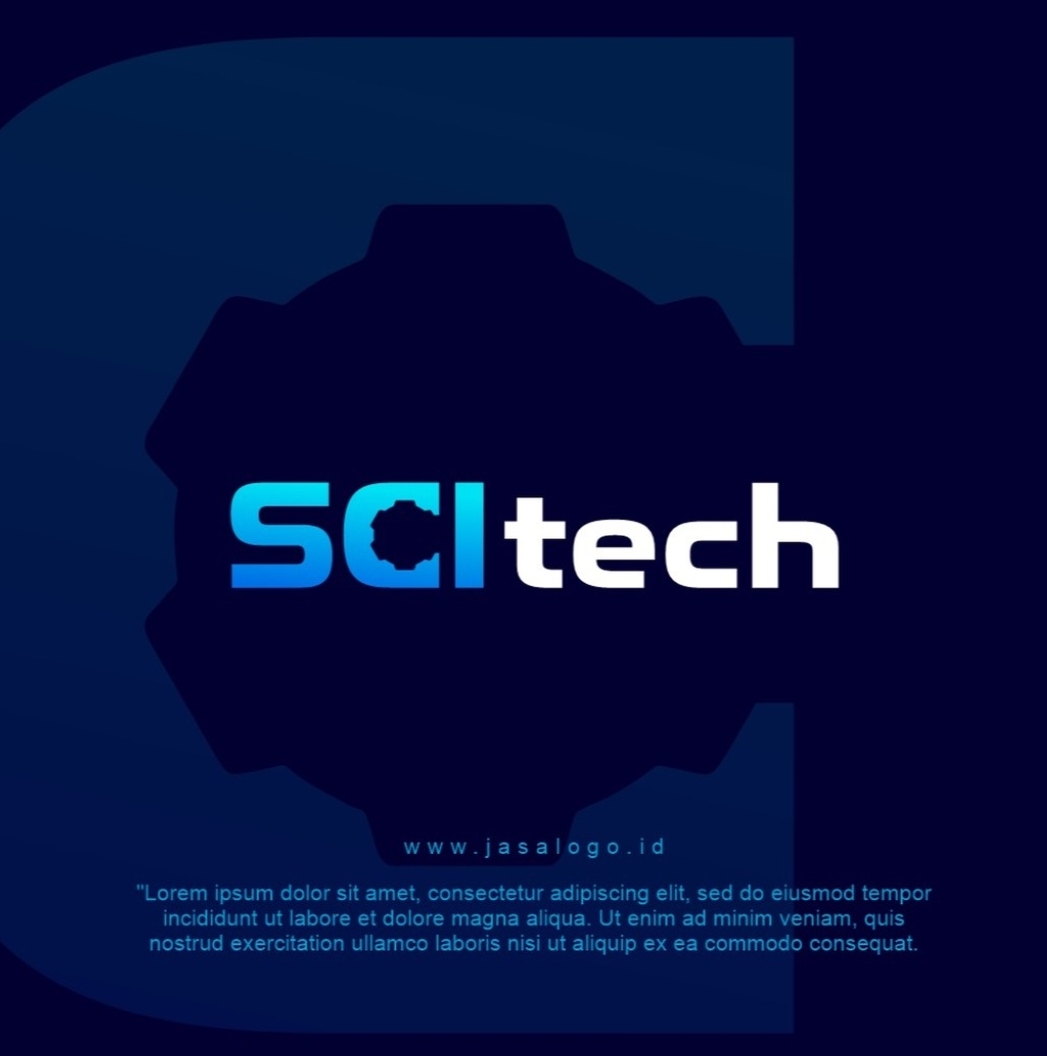
Desain logo harus memiliki gaya font yang relevan sehingga bisa mencerminkan identitas merek serta jenis brand dengan baik. Ada banyak pilihan gaya font untuk berbagai jenis brand dan karakternya seperti tebal, tipis, miring hingga unik. Untuk digunakan dalam desain logotype, ada banyak rekomendasi font yang menarik dan mencitrakan identitas brand.
Biasanya rekomendasi font untuk desain logotype akan mengutamakan keterbacaan dan bentuk huruf yang menciptakan kesan sesuai jenis brand. Brand yang menggunakan logotype bertujuan untuk membangun identitas yang kuat dengan membuat audiens mengingat nama brand. Untuk itu pemilihan gaya font untuk brand yang sering menggunakan logotype harus dipertimbangkan dengan baik.
REKOMENDASI GAYA FONT UNTUK JENIS LOGOTYPE SEUSAI BRAND
Untuk menciptakan desain brand yang bisa merepresentasikan brand dengan baik penting untuk memilih jenis font dan gaya font yang sesuai citra brand. Bahkan dalam bidang yang sama jika produk brand berbeda akan membutuhkan jenis font yang berbeda. Berikut beberapa rekomendasi font untuk desain logotype yang sesuai jenis brandnya:
- Rounded font untuk Logo Minuman
- Bold and Clean untuk Logo Teknologi atau perusahaan
- Sertif Elegan untuk Logo Fashion and Beauty
- Script untuk Logo Wedding dan Jewelry
- Wavy font untuk brand minuman
- Sans serif untuk Logo Perusahaan
- Condensed untuk Logo Teknologi
Beberapa rekomendasi tersebut hanya memilih gaya font yang paling digunakan dan sering ditemui untuk setiap brand tersebut. Terkadang brand bisa memilih gaya font yang tidak umum untuk tampil beda seperti penggunaan font serif elegan untuk minum segar. Pemilihan font tidak hanya berdasarkan jenis produk atau brand tetapi juga berdasarkan identitas merek.
CIRI FONT SETIAP JENIS BRAND
Ada banyak sekali jenis brand yang menggunakan jenis logotype, setiap brandnya memiliki ciri khas font tersendiri untuk mencerminkan identitas bisnis. Pemilihan gaya font akan cukup memengaruhi kesan dan pesan yang ingin disampaikan melalui logotype. Setiap jenis brand akan memiliki ciri-ciri atau karakteristik font yang cocok dengan citra brand tersebut.
Brand Makanan
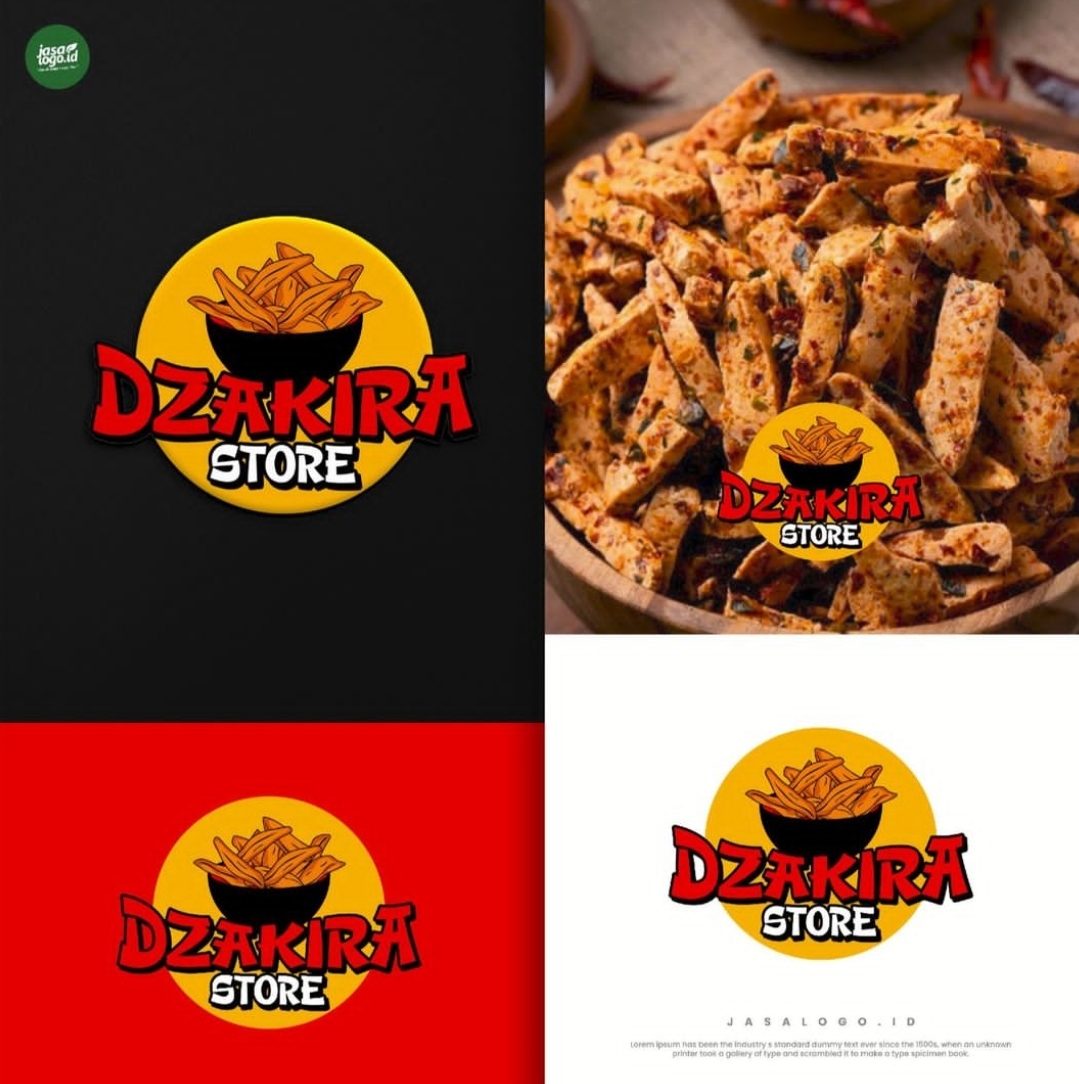
Font yang digunakan dalam desain logo biasanya akan digunakan untuk berbagai kebutuhan desain merek sehingga akan menjadi identitas merek. Untuk brand makanan gaya font yang bisa merepresentasikan bisnis mereka biasanya yang tebal, bersih dan bulat. Terkadang beberapa ada yang menggunakan font tebal yang kaku tetapi yang mudah dibaca.
Beberapa font yang cocok untuk brand makanan seperti:
- Font Tebal dan Bulat
- Bold and Sharp Font
- Elegan untuk Bakery
- Retro and Bold Outline untuk Snack
Pemilihan jenis font harus menyesuaikan juga dengan jenis produk agar mencerminkan jenis bisnis makanan dengan baik. Jika makanan resto atau makanan berat biasanya memiliki logo yang unik dan mencolok. Sementara bisnis makanan dessert lebih cocok dengan menggunakan font script atau serif yang elegan.
Brand Minuman
Untuk brand minuman, font yang digunakan biasanya memiliki ciri yang sederhana, ramah dan tampil menyenangkan. Font untuk brand minuman tidak tampil sekaku dan semonjol font brand makanan. Untuk ciri font yang cocok untuk brand minuman sebaiknya memiliki:
- Huruf yang mudah dibaca
- Font unik agar tampil beda
- Tampil segar dan ramah
- Memiliki gaya sesuai jenis minuman
Beberapa font yang cocok untuk brand juga perlu menyesuaikan jenis produk dan identitas mereknya, seperti:
- Font Bulat yang Ramah untuk Brand Minuman Segar
- Script Tipis untuk Brand Minuman Kopi
- Display Font untuk Brand Minuman Segar
- Font Serif dan Sans serif Tipis untuk Brand Wine atau Minuman Premium
Jenis produk dan citra yang ingin diciptakan merek akan dijadikan pertimbangan dalam memilih gaya font yang tepat. Brand minuman segar harus menggunakan gaya font yang ramah, unik dan berkesan menyenangkan. Beberapa brand minuman juga bisa tampil elegan jika brand ingin memiliki citra premium seperti beberapa brand kopi dan wine.
Brand Fashion
Berbicara soal brand fashion biasanya ini juga menyesuaikan dengan jenis fashion yang dipasarkan merek tersebut. Beberapa jenis fashion bisa memiliki tampilan elegan, mewah, sederhana dan ada juga yang sporty dan fun. Secara umum bisnis fashion akan menggunakan desain logo lettermark atau wordmark dengan beberapa ciri font ini:
- Font Mudah Terbaca dan Bersih
- Sesuai dengan Jenis Fashion
- Merepresentasikan Kesan Brand yang Terpercaya
Sementara untuk beberapa font yang cocok untuk desain logo Fashion seperti:
- Gaya serif untuk Fashion Dress Elegan
- Sans serif untuk Casual Wear atau Sporty Fashion
- Bulat dan Ramah untuk Brand Fashion Anak-anak
Pastikan untuk menyesuaikan jenis fashion dan identitas merek agar logo mencerminkan terlihat profesional. Jika gaya font tidak sesuai jenis fashion ini bisa menciptakan kesan kurang profesional dan kurang terpercaya.
Desain logo untuk setiap brand bisa memiliki ciri khas dan karakteristik yang berbeda termasuk dalam pemilihan fontnya. Brand yang sering menggunakan logotype akan memilih gaya font yang bisa mencerminkan jenis brand dan citra merek dengan baik. Setiap brand makanan, minuman teknologi hingga kecantikan akan memiliki ciri gaya font yang berbeda agar relevan dengan citra setiap brand. Beberapa brand mungkin ingin memiliki desain logotype yang mudah terbaca sehingga menggunakan font bersih. Sementara brand makanan yang menggunakan desain logotype sering memilih font tebal untuk tampil mencolok.